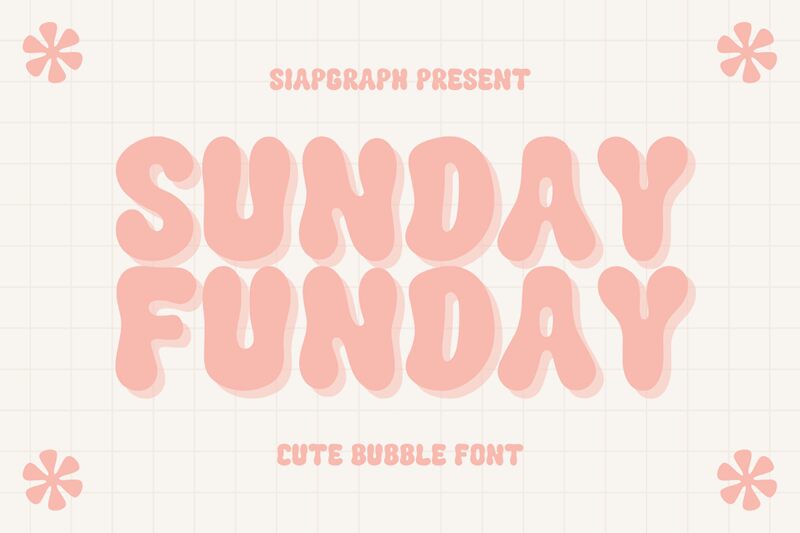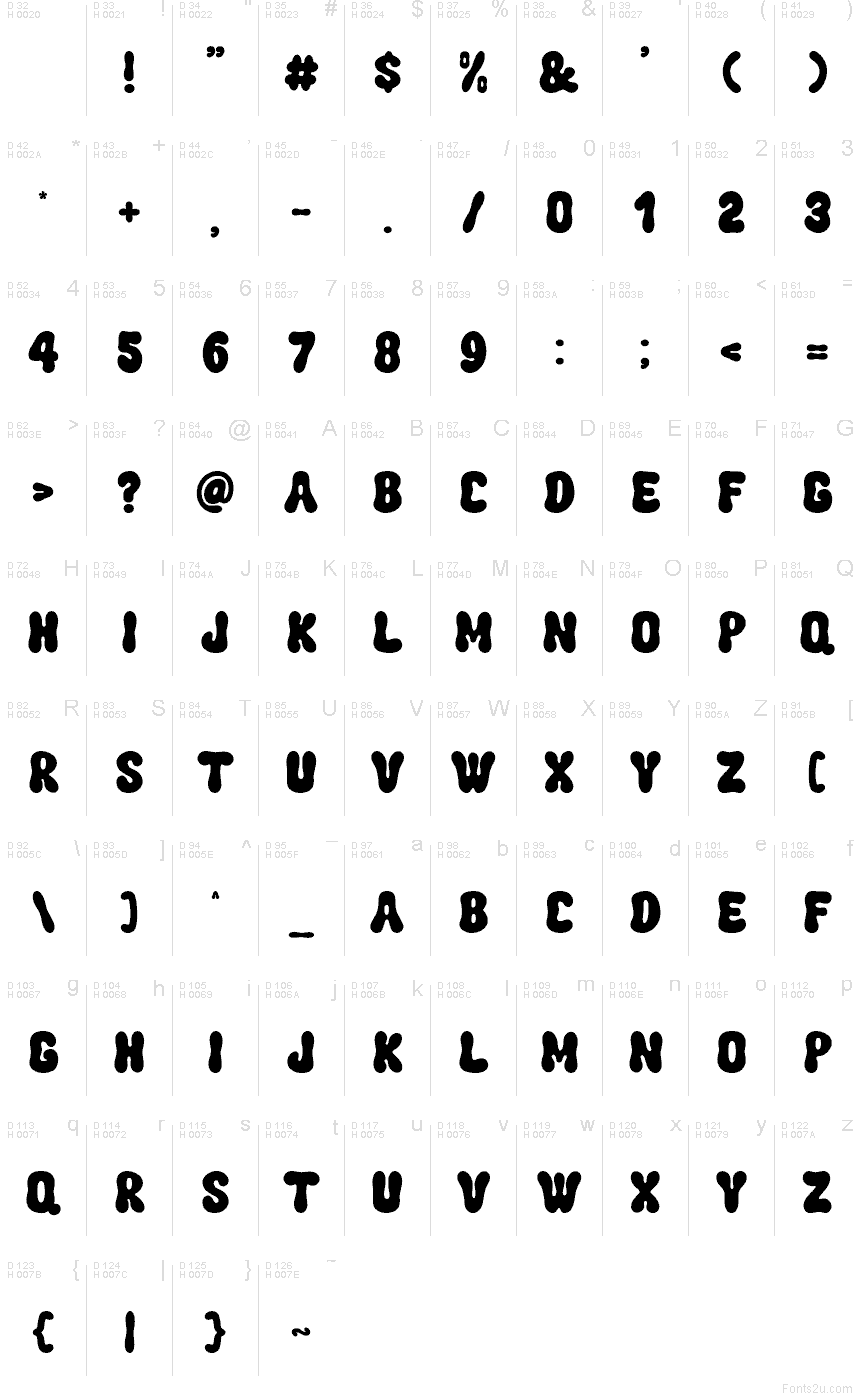
Sunday Funday od SiapGraph Studio je bezplatný groovy font typu display, který zaujme svými křivkami připomínajícími lávovou lampu a hlubokými, zaoblenými zářezy. Díky nim působí písmo měkce a pružně. Široká silueta udržuje design kompaktní a výrazný, zatímco vnitřní vybrání jej odlišují od běžných „bublinových“ stylů.
Svou hravostí se skvěle hodí na párty letáky, dětské obaly, samolepky, záhlaví na sociálních sítích nebo veselá menu do kaváren – tedy všude tam, kde písmo funguje jako grafický prvek. Nejlépe vynikne u krátkých titulků a brandingu, protože jeho masivní křivky vytvářejí zábavný rytmus bez nutnosti dalších ozdob.